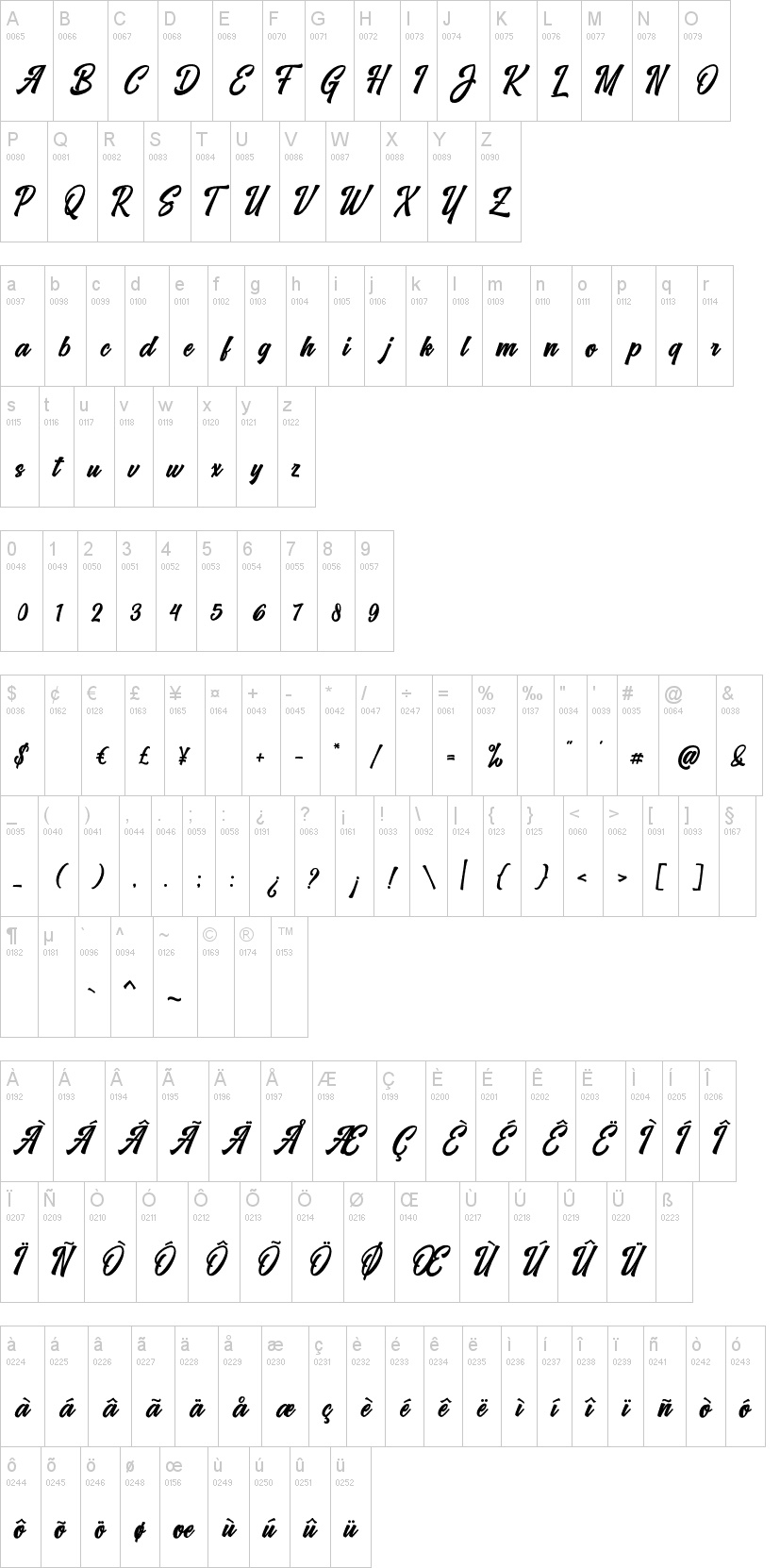
Vrindals Script 是一款灵动而又有趣的手写字体,它具有清晰的笔触,自然的流动,以及明快的节奏,可以让您的文字更加生动有趣。它可以用于各种应用,例如海报、标识、标签、标题、书籍封面、社交媒体等。Vrindals Script 字体可以让您的文字看起来更加自然,更加有趣,而且它还具有多种字体样式,可以让您根据您的需求来调整字体的外观。内容介绍
Vrindals Script是一款非常不错的手写艺术字体,具有很好的视觉感,适合于文化类的宣传设计、商业类品牌的广告和产品包装设计以及个性化文字排版等较多场景。